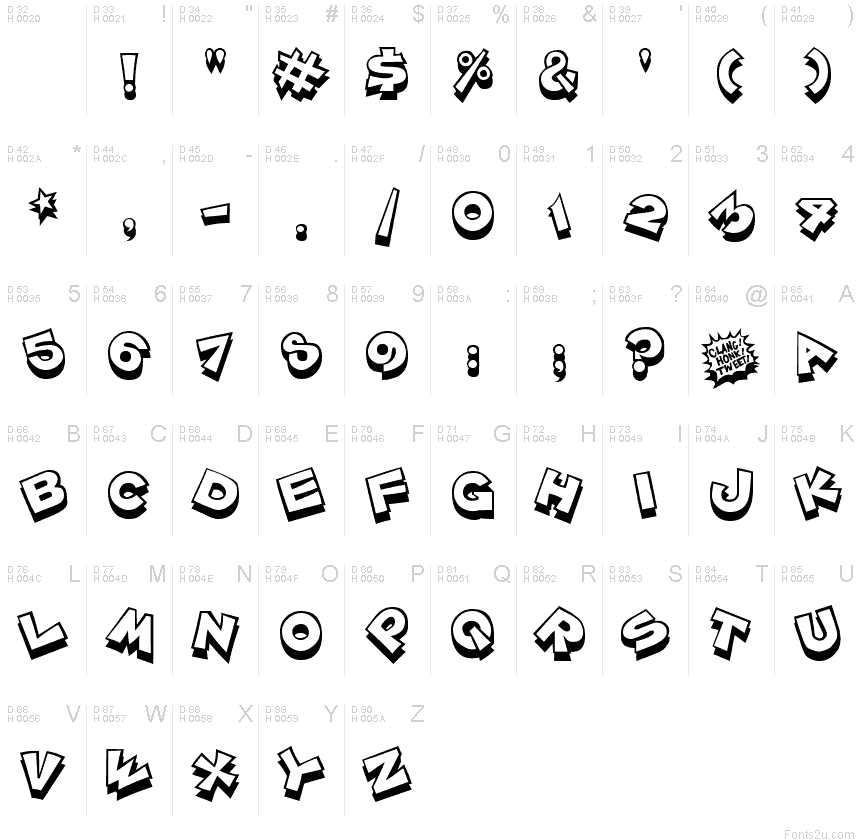
ZoinkFat, eine kostenlose Comic-Display-Schrift von Marty Yawnick (Type A), versprüht sofort die laute Energie von Cartoons der frühen 90er-Jahre. Die Buchstaben wirken wie aus kühnen, gezackten Formen ausgeschnitten und schräg auf die Seite geworfen; dazu kommt ein dicker, versetzter Schatten, der den Großbuchstaben den Punch eines Aufklebers oder eines Comic-Panels verleiht.
Es passt perfekt für Plakate, Zine-Cover, Game-Titel, Comic-Soundeffekte und kurze Merch-Grafiken, bei denen ein paar Worte einen ordentlichen Schubs brauchen. Als kostenlose Schriftart eignet sie sich zudem hervorragend für Flyer-Überschriften, Cover-Lines und Monogramme, da die klobige Silhouette und die übertriebene Schräglage schon die meiste Arbeit erledigen, bevor man überhaupt etwas anderes hinzufügt.